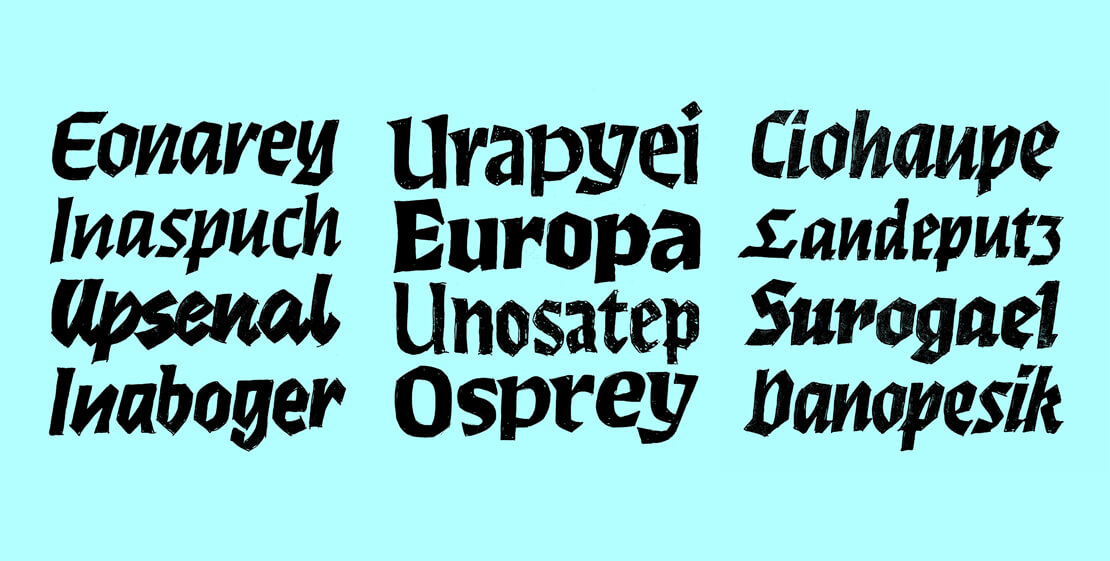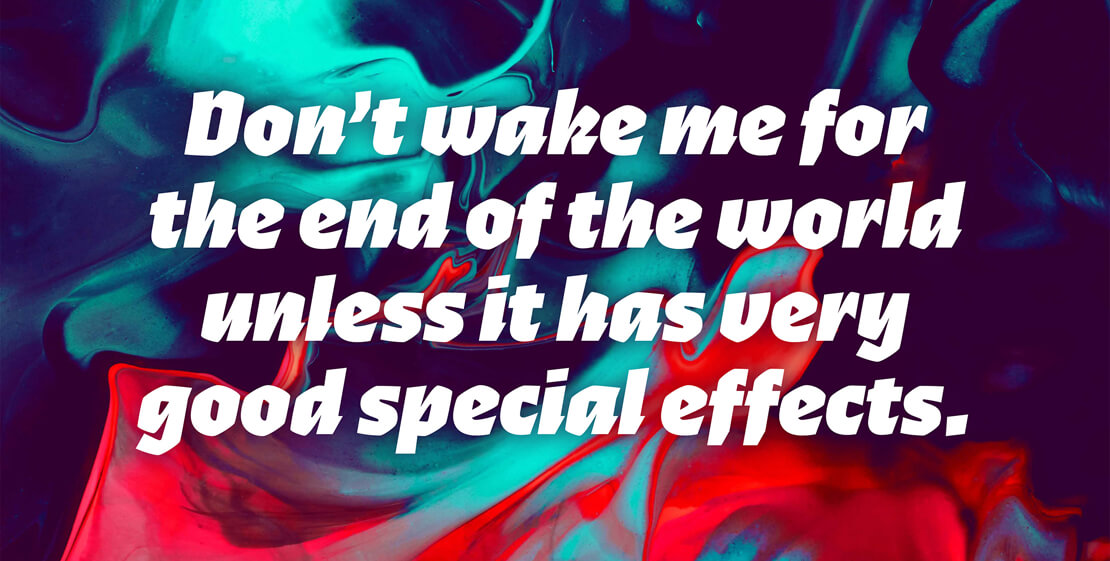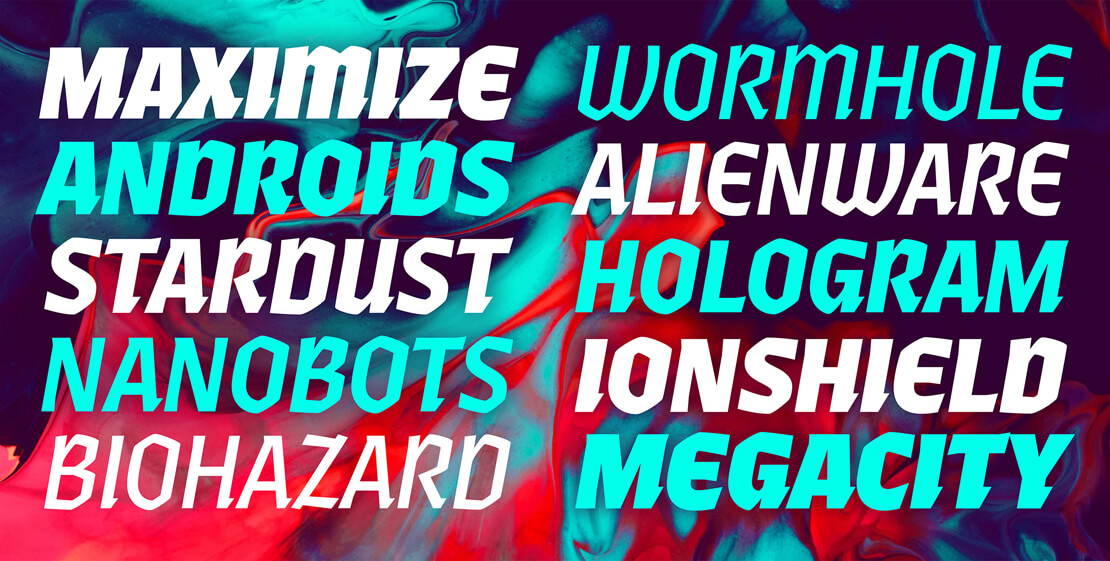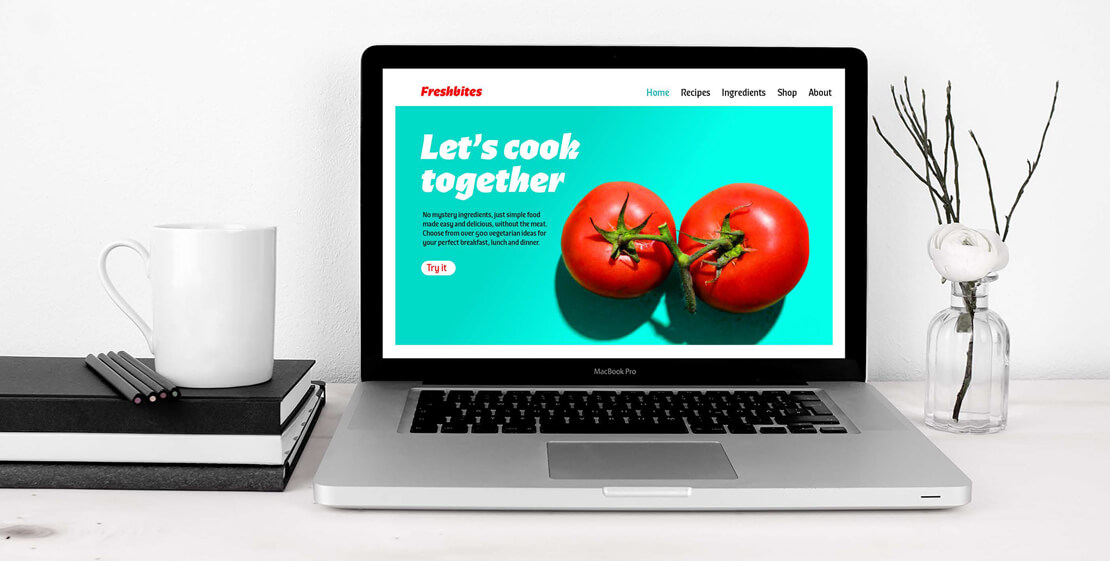
Ferryman – Ausdrucksstarke Display-Schrift von Felix Braden
Rechtzeitig zur Halloween-Zeit präsentiert Felix Braden seine neueste Kreation. »Ferryman« ist eine Gebrochene Schrift mit zeitgenössischer Lesbarkeit. Sie stellt eine Antithese zu den überstrapazierten geometrischen Serifenlosen und Neo-Grotesken dar.
Bekanntlich haben Gebrochene Schriften öfters damit zu kämpfen, dass sie schwer zu entziffern sind. Der Kölner Type-Designer Felix Braden hat die Halloween-Zeit als Anlass genommen, dieses zu ändern und präsentiert nun eine umfangreich ausgebaute und 18 Schnitte umfassende Schriftfamilie.
Entstehungsprozess von »Ferryman«
Das eigentliche Ziel von Ferryman war nicht, eine historisch korrekte Gebrochene Schrift zu kreieren, sondern vielmehr, Buchstaben zu gestalten, die in der heutigen Zeit leicht lesbar sind und als zusammenhängende Schriftfamilie funktionieren.
Um dies zu erreichen, wurden lesefreundliche Formen historischer Schriften mit Antiqua-Elementen kombiniert und eine Vielzahl von Alternativbuchstaben integriert, um die Benutzerfreundlichkeit zu optimieren.
Ferryman stellt außerdem ein eher seltenes Beispiel für eine Gebrochene Schriftfamilie mit einer Kursiven dar. Bei seiner Recherche hatte Felix Braden jedenfalls historische Kursivschriften entdeckt, die ansprechend mit dem Wesen der Gebrochenen Schriften harmonieren. Diese Inspirationen stammen hauptsächlich aus kalligrafischen Ansätzen und Handletterings. Bei Ferryman konnten sie schließlich zu einer funktionierenden kursiven Satzschrift adaptiert werden.